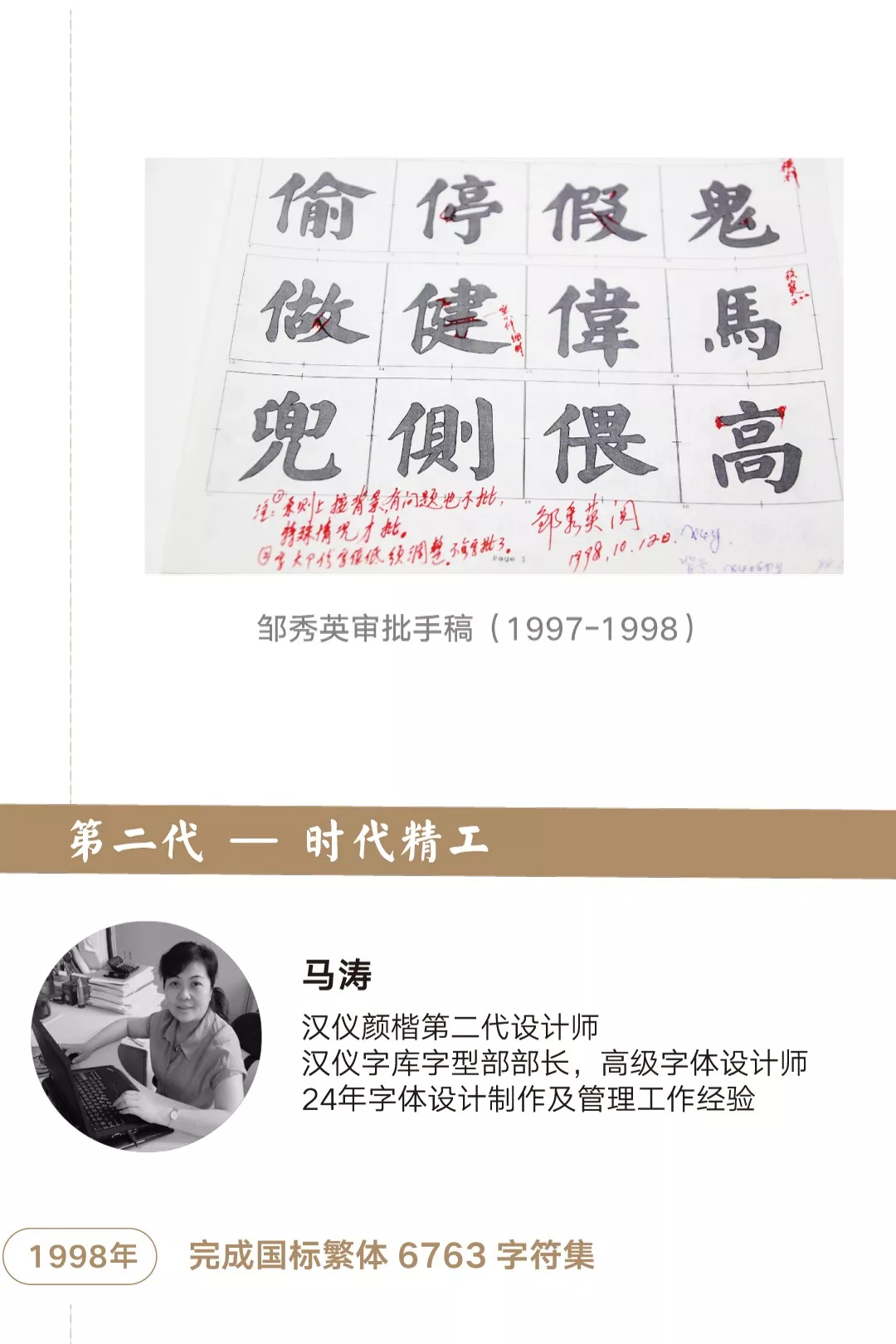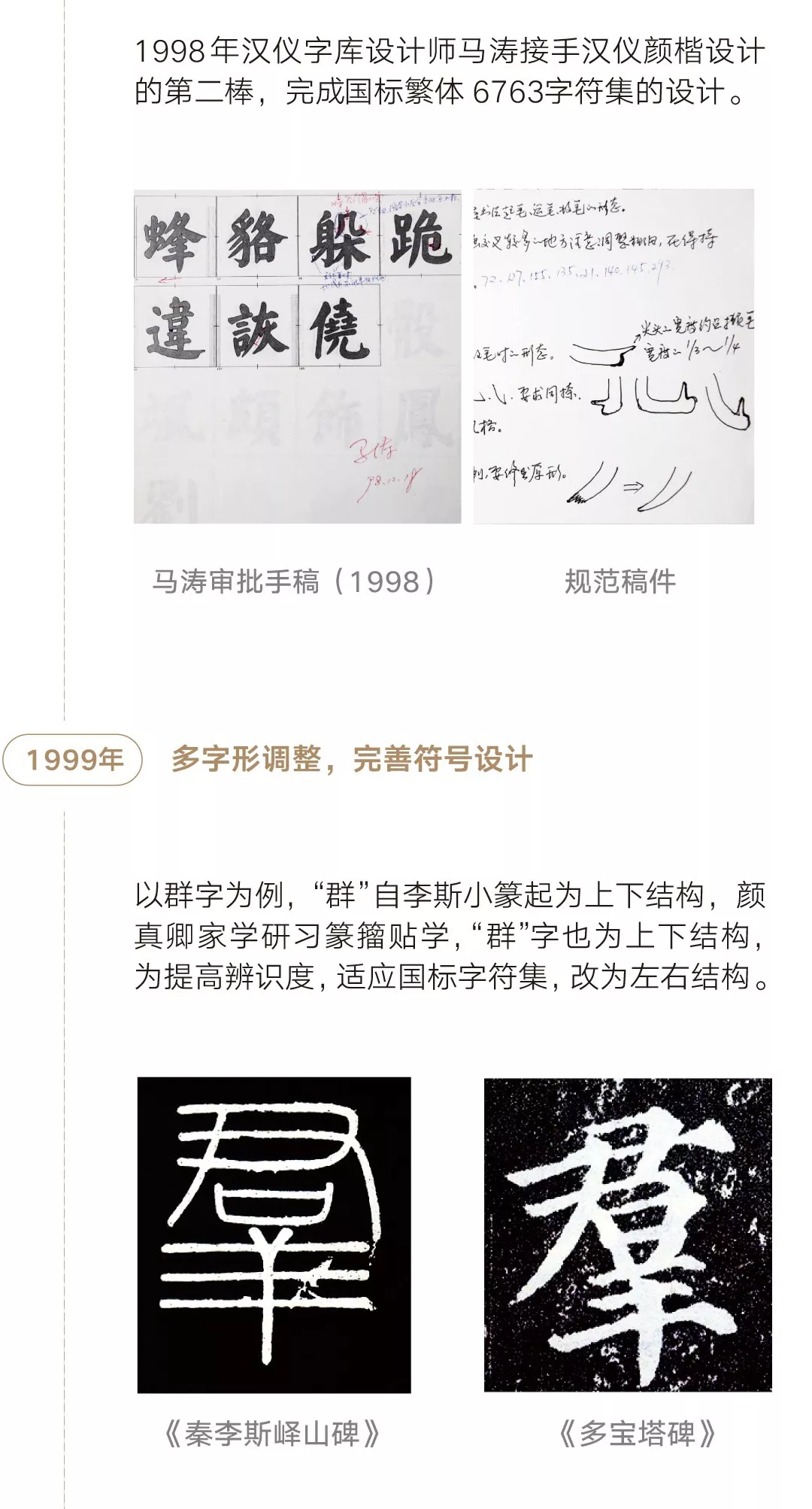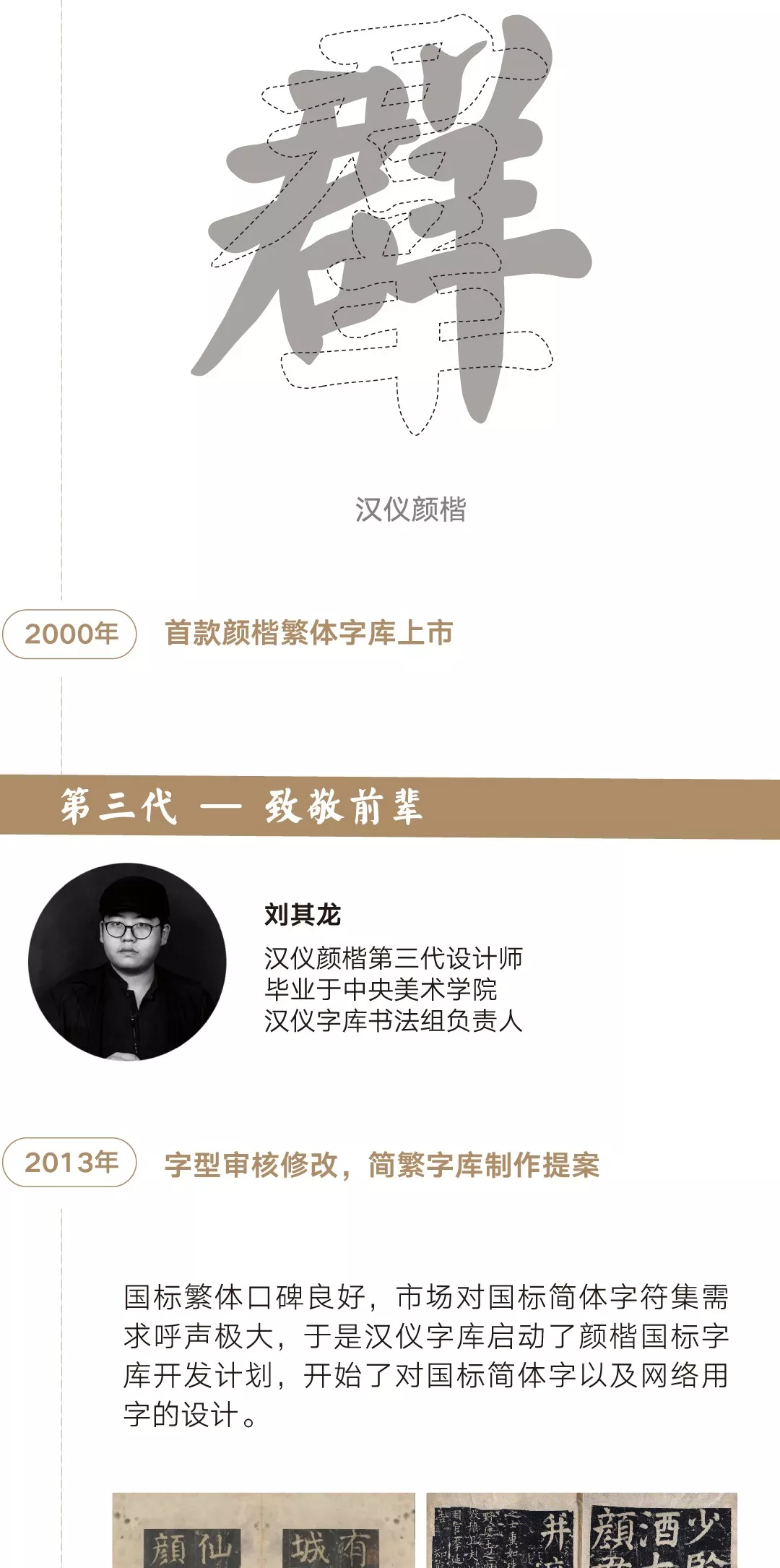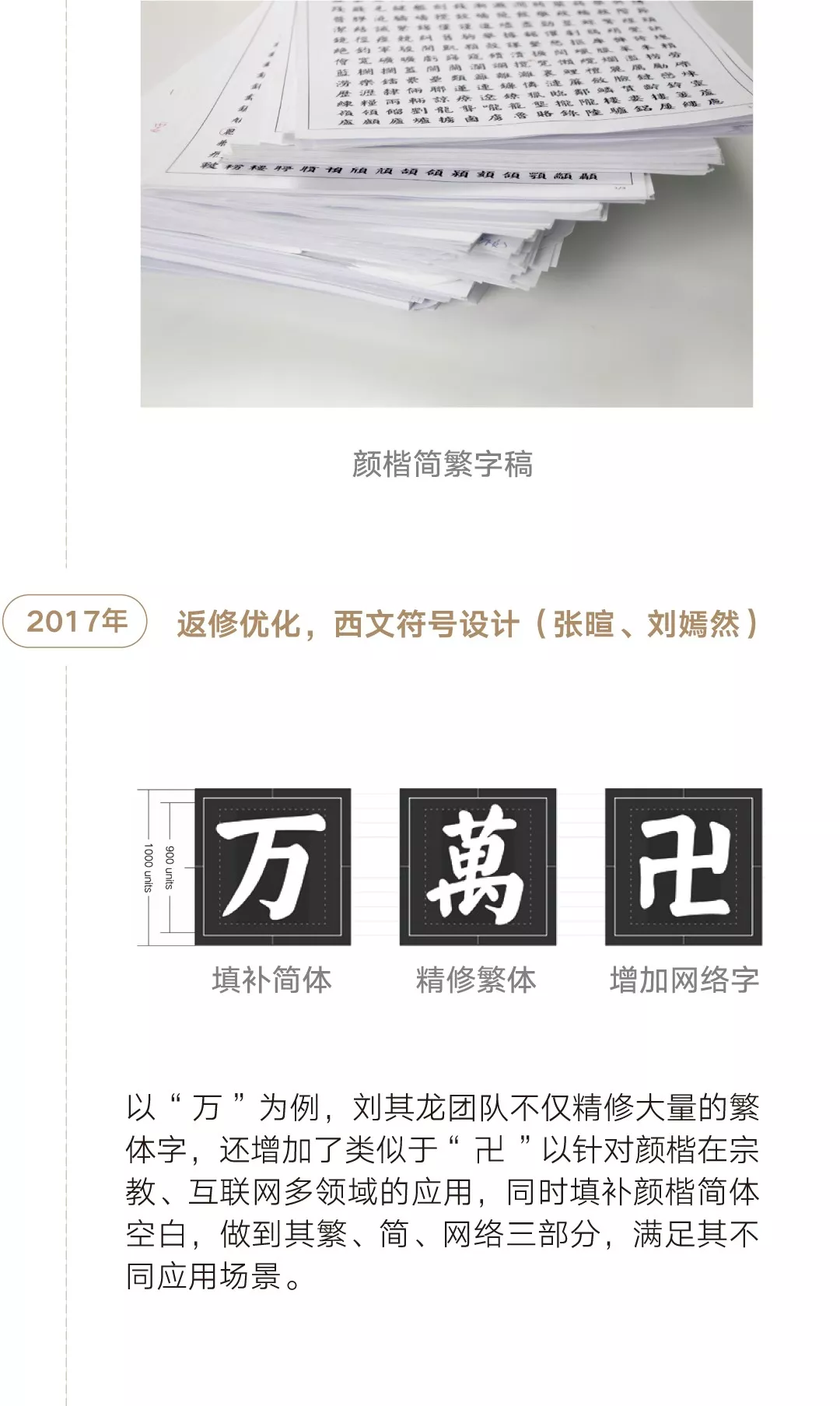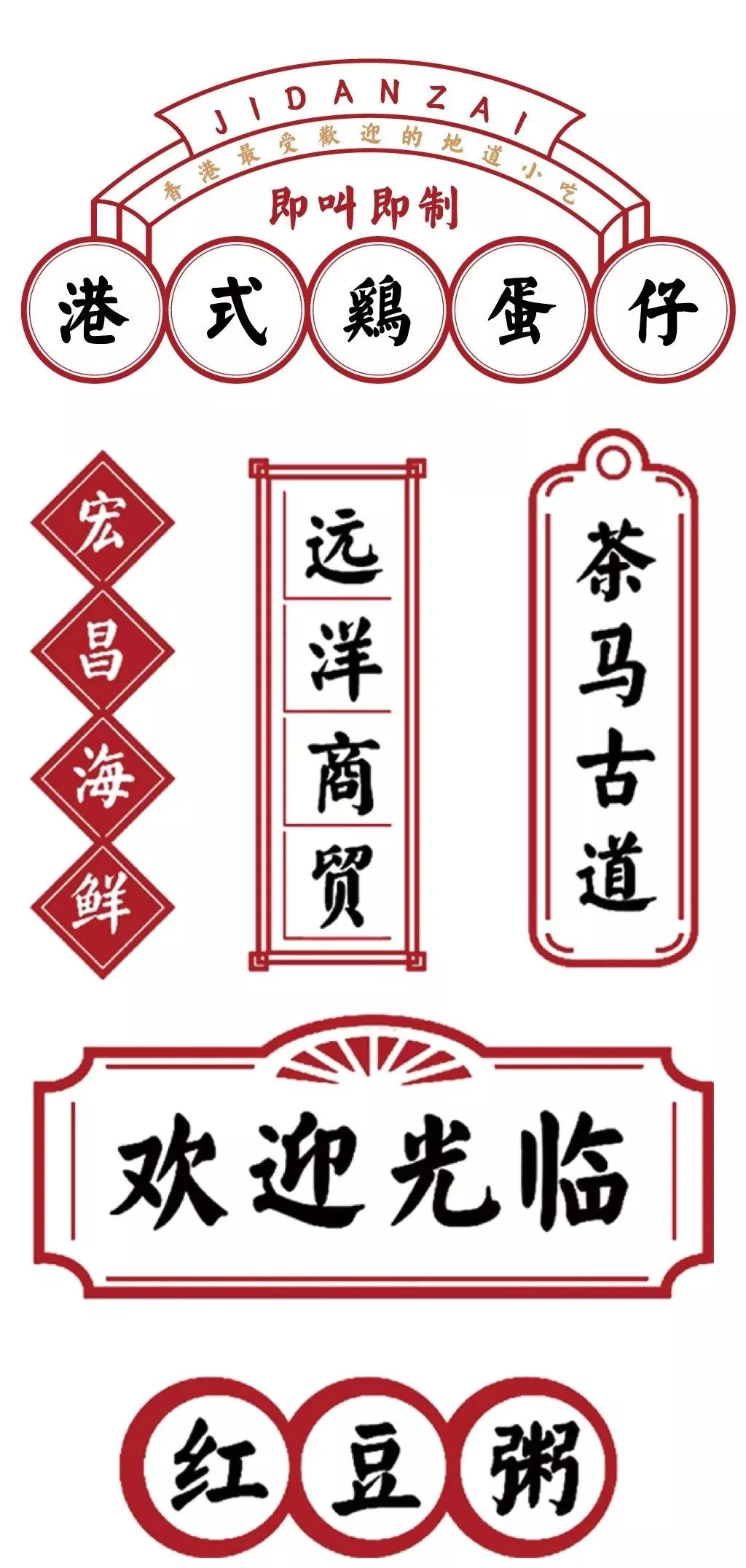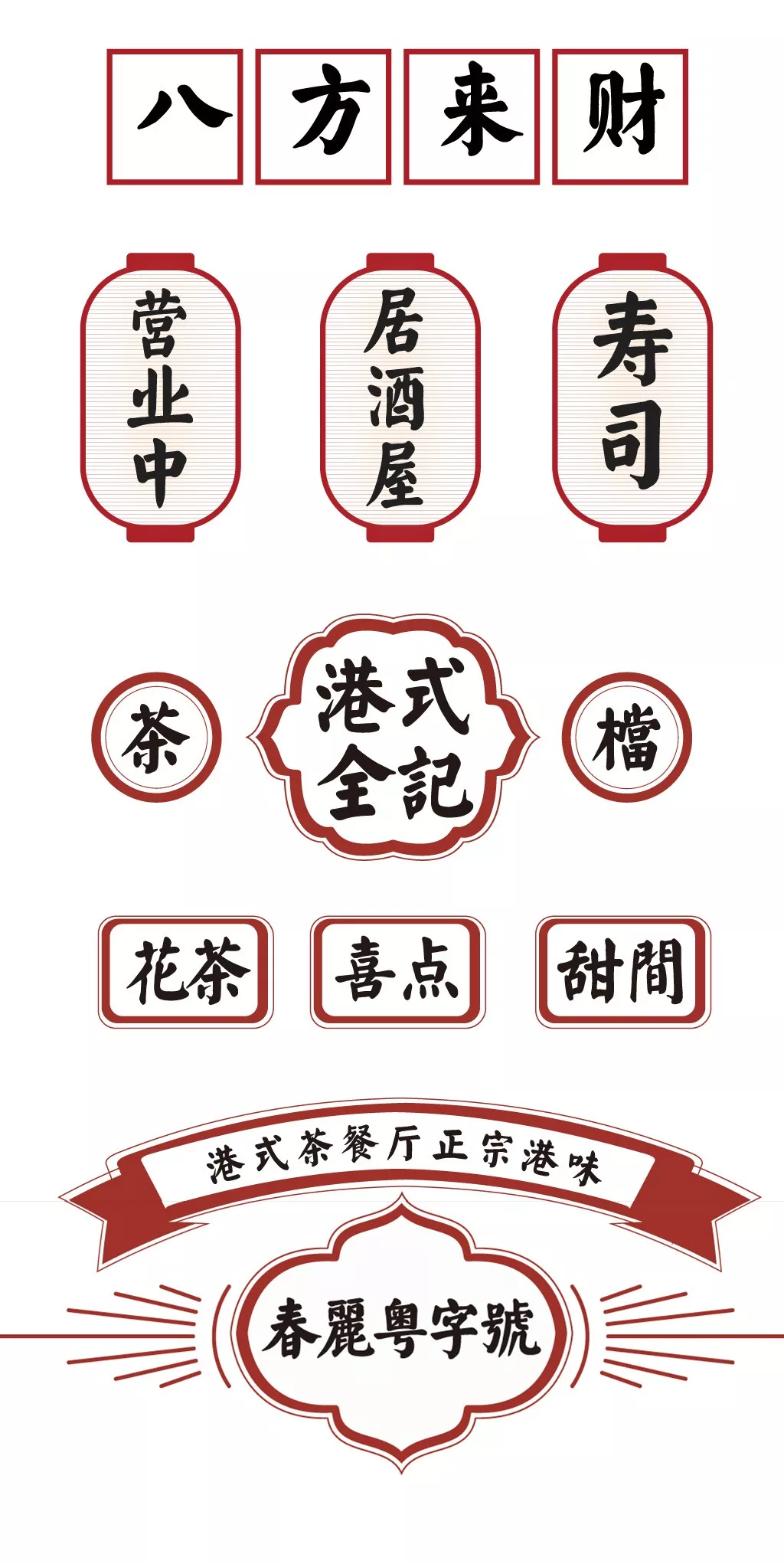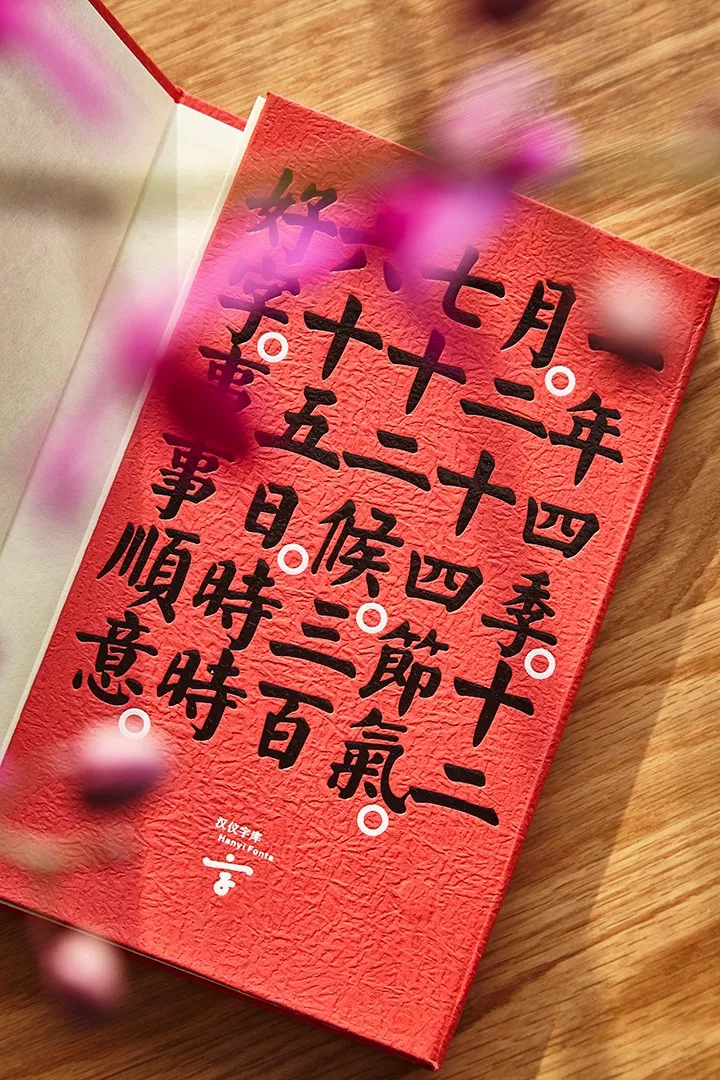
汉仪颜楷字体介绍,汉仪颜楷设计灵感
颜楷,即颜真卿的楷书,颜真卿(709年-784年)对中国书法有很深远的影响,他与柳公权并称“颜柳”,有“颜筋柳骨”之誉,传世之作《祭侄文稿》是公认还存于世间的“天下第二行书”,其《多宝塔碑》作为中小学生必修书法教材,被教育部推荐,是众多初学书法者的首选。
教育部书法教材推荐碑帖范本
颜真卿的真书雄秀端庄,方中见圆,具有向心力,用笔浑厚强劲,善用中锋笔法,饶有筋骨,亦有锋芒,大气磅礴,多力筋骨,具有盛唐的气象。
颜楷是民族文化的瑰宝,更是文化发展史上的一颗璀璨明珠,汉仪秉承文化传承的精神与民族责任感,自1997年就着手对颜真卿楷书的研究与再设计,历经20余年三代设计师的不断努力,终于完成了9000余字的设计。